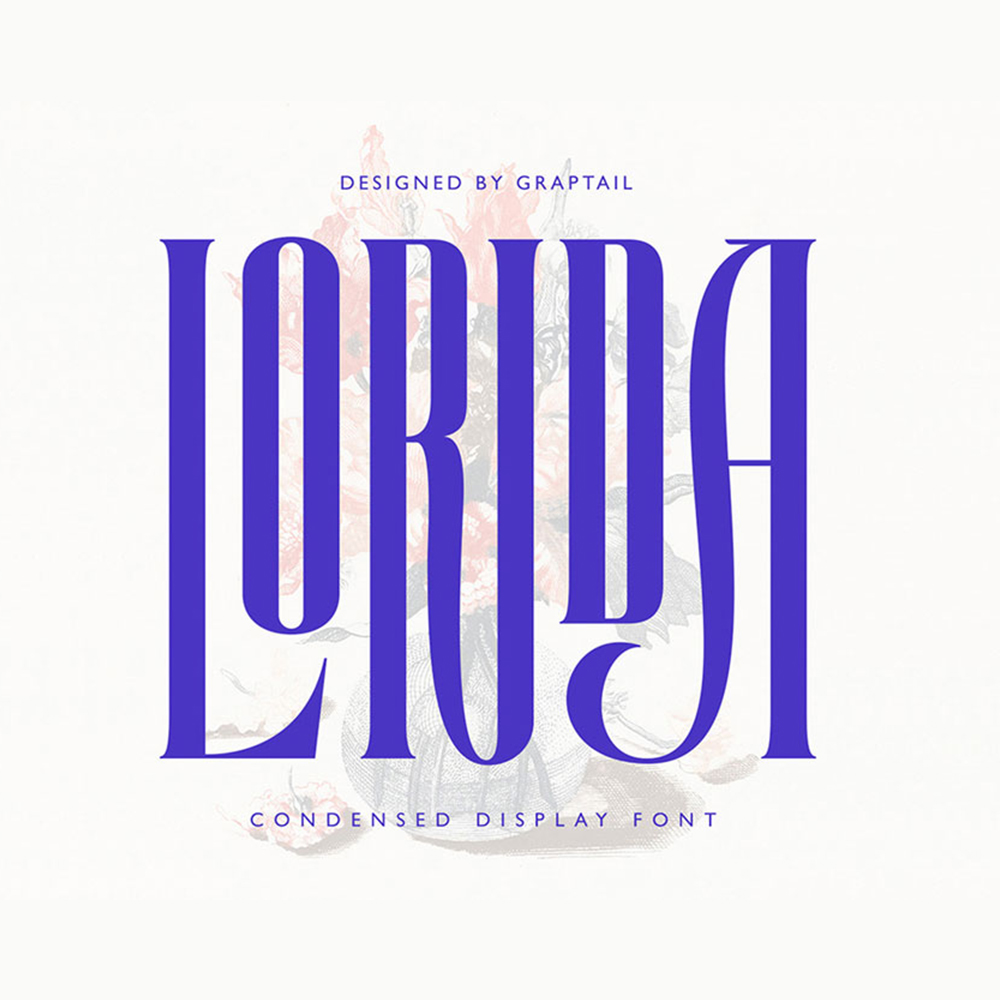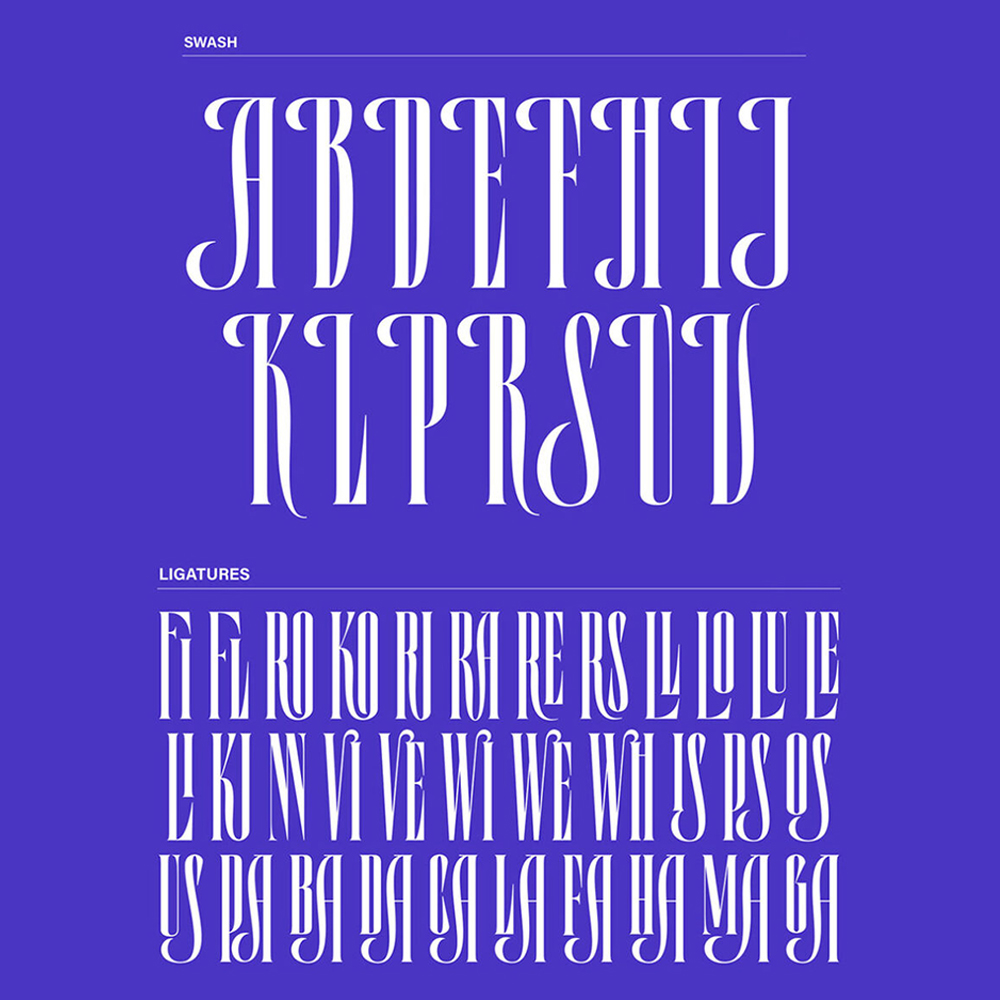
فونت پرمیوم و انگلیسی Lorida Font یک فونت سریف فشرده با ظاهری قدیمی اما مدرن است. این فونت بر اساس یک فونت فشرده و یکپارچه با ترکیب سبکهای مختلف ساخته شده است. همچنین به سادگی کاراکترهای جایگزین را با استفاده از Character Map (ویندوز)، Font Book (مک) یا یک برنامه نرمافزاری مانند PopChar (برای ویندوز و مک) جایگذاری کنید. این فونت مناسب برای لوگو، کارت تبریک، نقل قول، پوستر، برندسازی، کارت ویزیت، کارت پستال، عنوان فیلم، هدر وبلاگ، نقل قولهای هنری، تایپوگرافی، مجلات و موارد دیگر.